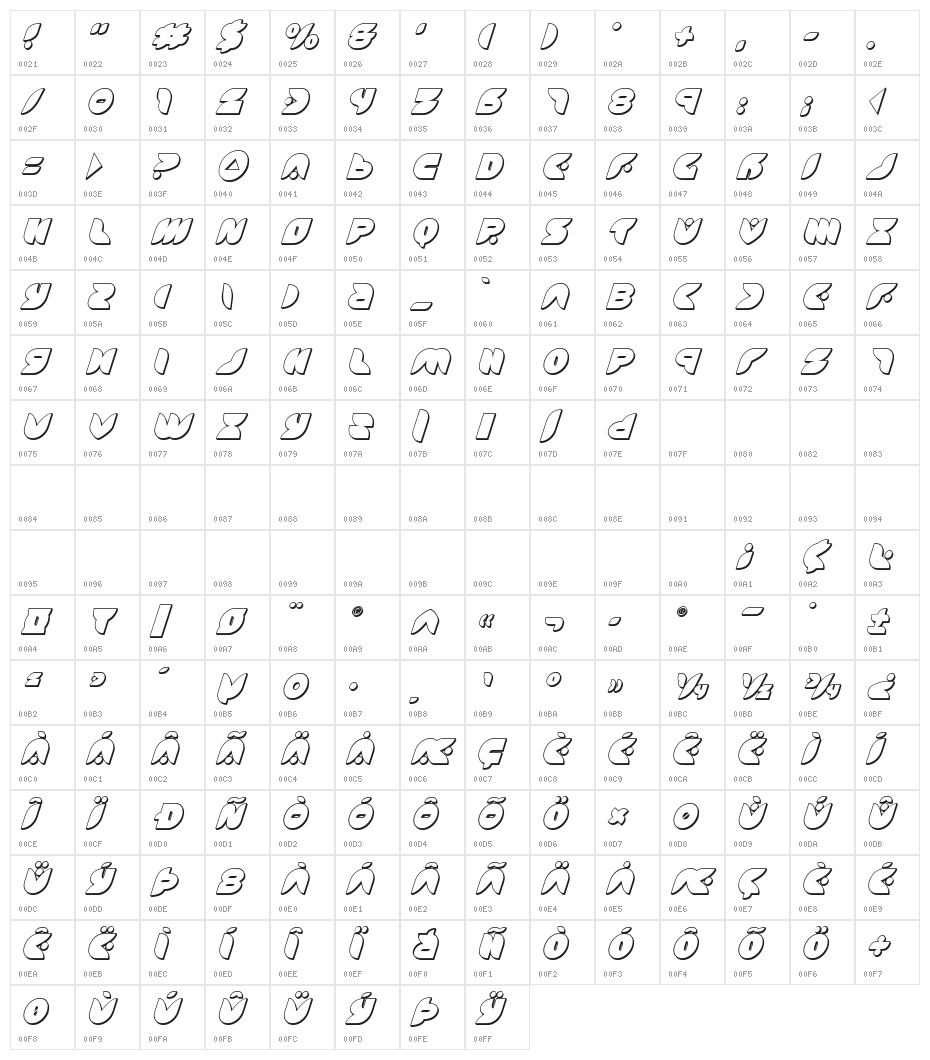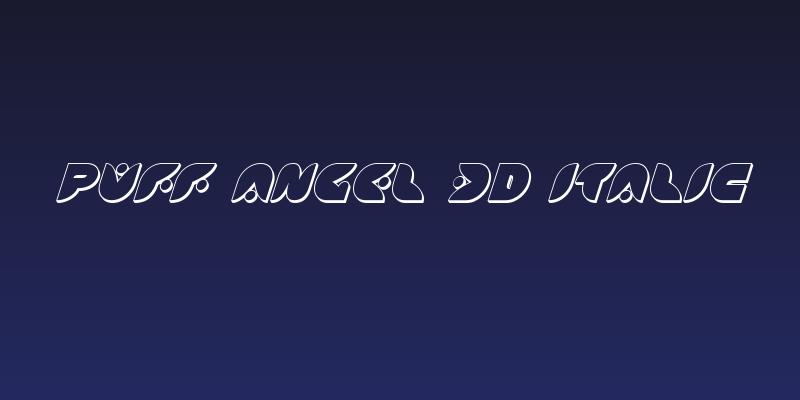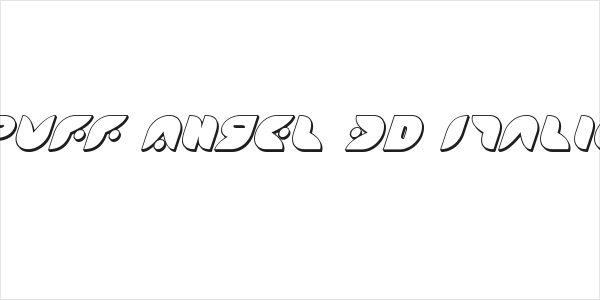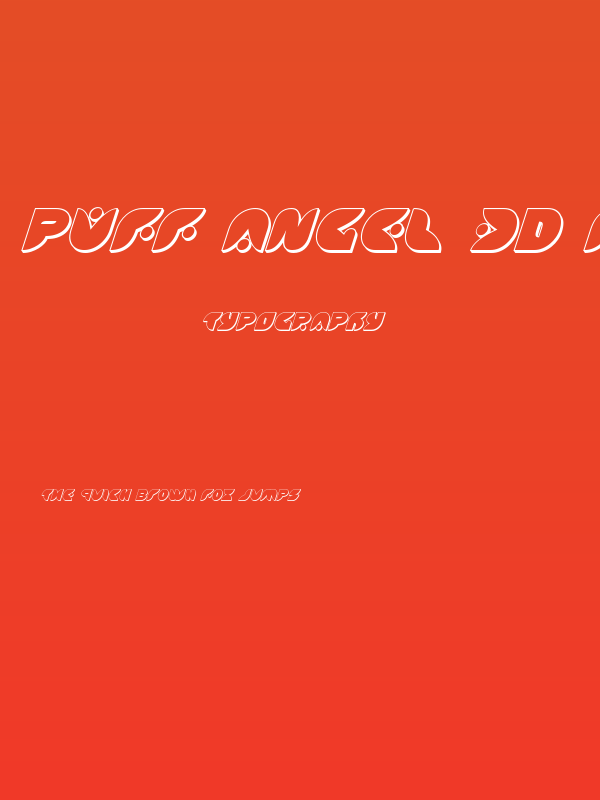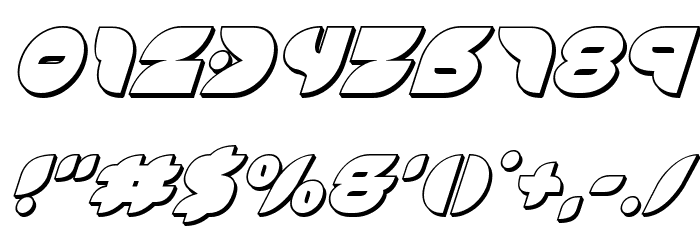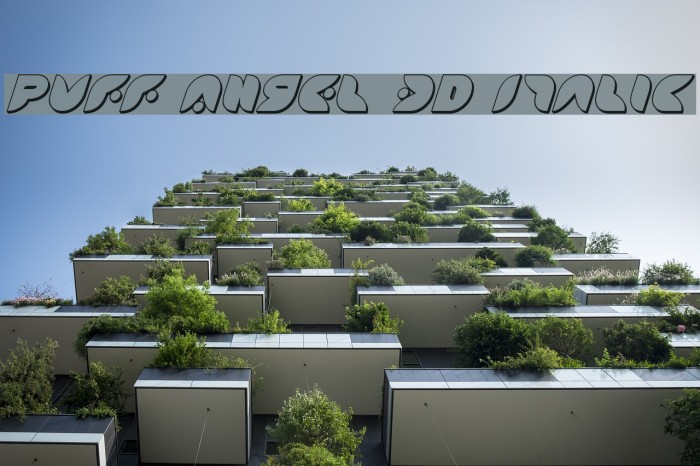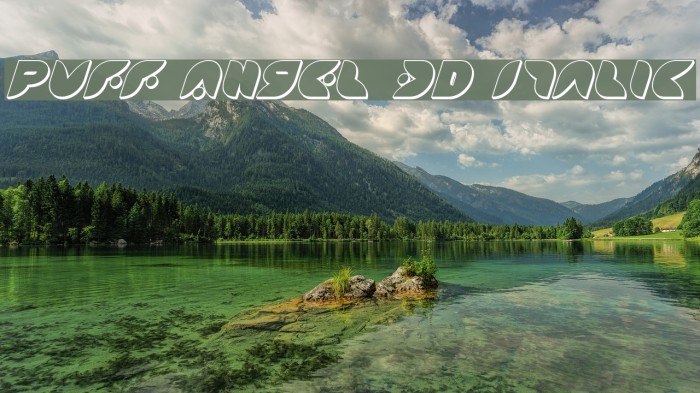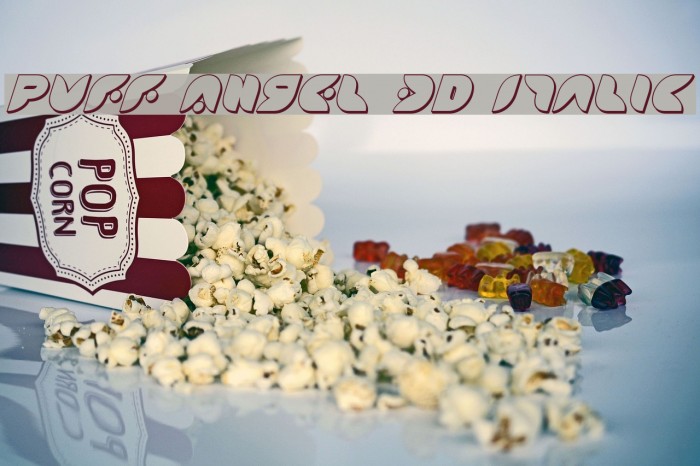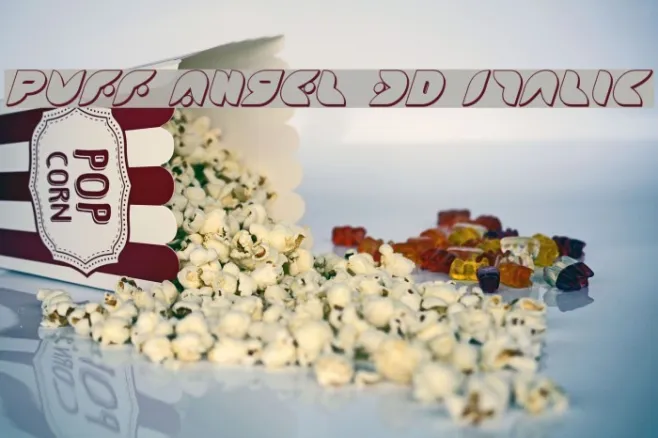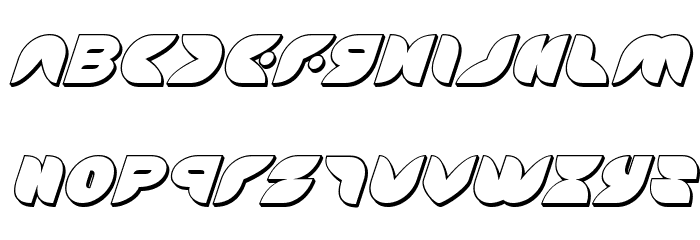
Puff Angel 3D Italic Font
| Estilo general | Modern, Decorative |
| Proyectos propuestos | Ideal for children's books, playful branding, vibrant posters, and creative designs. |